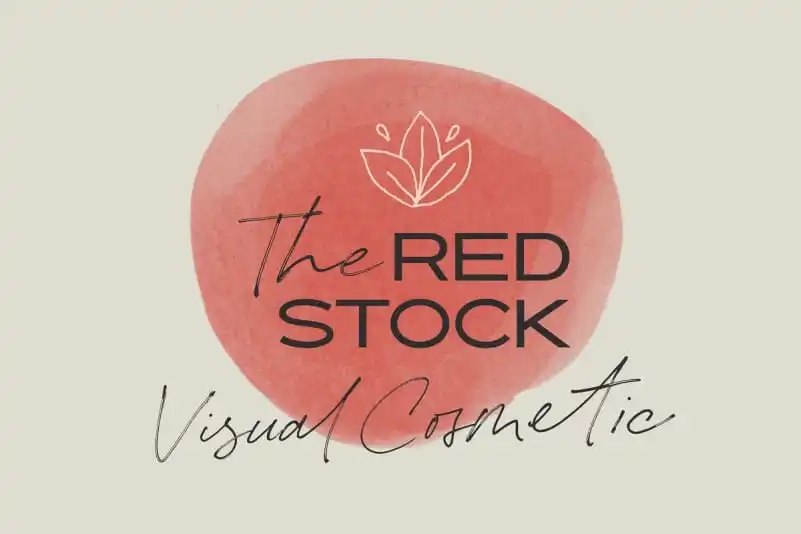
The Redstock Handwritten Font – Download Grátis
Na categoria de Script Fonts, a fonte “The Redstock” traz uma experiência visual única e sofisticada, perfeita para personalizar logomarcas, criar identidades de marca ou mesmo criar assinaturas elegantes para projetos diversos. Esta fonte foi criada com um toque autêntico da mão humana, mantendo o naturalismo em cada traço, que proporciona um efeito elegante e grandioso. O design é perfeitamente adaptado para uso em logotipos ou identidades de marca, oferecendo uma opção diferente do que muitas outras fontes disponíveis. Imagine a “The Redstock” como um cosmético visual: cada traço tem um toque quase neutro de tinta-peteca, criando um efeito arredondado perfeito. Esta característica torna a fonte ainda mais natural e fluida, oferecendo uma versatilidade incrível em todas as aplicações – seja para criar um logotipo sofisticado ou apenas escrever seu nome com estilo. A “The Redstock” traz o poder da personalização ao seu trabalho de design, tornando-a uma escolha indispensável para quem busca expressar sua marca de forma única e elegante.